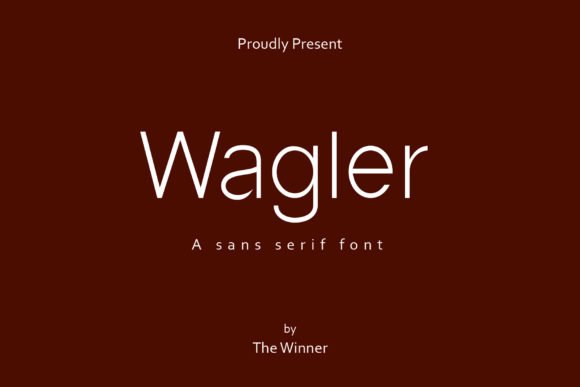
Wagler - это минимальный и аккуратный шрифт sans serif.
Его можно легко подобрать к невероятно большому набору проектов, поэтому добавьте его в свои творческие идеи и обратите внимание, как он их выделяет!